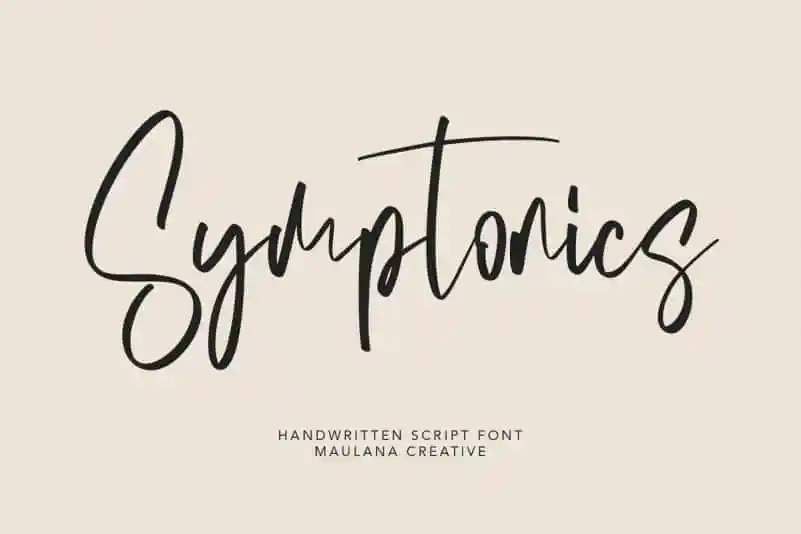
Symptonics Script Font – Download Grátis
A Symptonics Script Font é uma fonte criada com rapidez por Maulana Creative, inspirando-se na arte de desenhar a mão. Esta fonte foi escrita usando um pincel e preparada para obter resultados suaves e equilibrados. O design desta tipografia se destaca perfeitamente tanto no campo da assinatura quanto em materiais de correspondência, logomarcas ou designs de marca; também se adequa perfeitamente a elementos de layout para revistas, livros, cabeçalhos de sites e até mesmo ao estilismo de calçados. Esta fonte é perfeita tanto para aqueles que buscam um estilo elegante e sofisticado como para quem deseja algo mais descontraído e criativo. Com sua versatilidade, a Symptonics Script Font se encaixa em uma ampla gama de projetos gráficos, seja um trabalho profissional ou algo mais casual, transformando mensagens textuais em elementos visuais inovadores e memoráveis.